웹문서에 구글 폰트(Google Fonts) 적용하기
웹문서를 만들다 보면 웹문서용으로 사용할 '웹폰트(web fonts)'라는 것이 필요합니다. 물론 웹폰트를 적용하지 않더라도, Windows나 Mac 등의 시스템에서 사용하고 있는 기본 폰트를 통해 글자들이 보여질 수는 있겠지만, 디자인 의도가 적용된 폰트를 제대로 반영하지 못하게 됩니다.
CSS에서 세팅한 대로 적절한 폰트가 웹문서에 적용이 되지 않는 경우에는, 폰트가 차지하는 크기가 달라서 문단의 배치 등에도 좋지 않은 영향을 받을 수도 있습니다.
이처럼 웹문서 작성 시에는 분위기와 잘 어울리는 폰트를 사용하는 게 중요할 텐데요, 구글 폰트를 사용하게 되면 이와 같은 이슈를 아주 간단하게 해결할 수 있기 때문에, 거의 전세계의 웹 제작자들이 사용하고 있다고 보아도 무방합니다.
ZOMBTI, MBTI 이상형 여친 찾기 적용 사례
개인 프로젝트로 App을 만들 때에도 구글 폰트를 적용했습니다.
ZOMBTI(좀비티아이)의 경우에는 좀비 느낌을 줄 수 있는 폰트를 사용했고, MBTI 이상형 여친 찾기 앱에서는 귀엽고 둥근 느낌이 드는 폰트를 사용했더랬습니다.
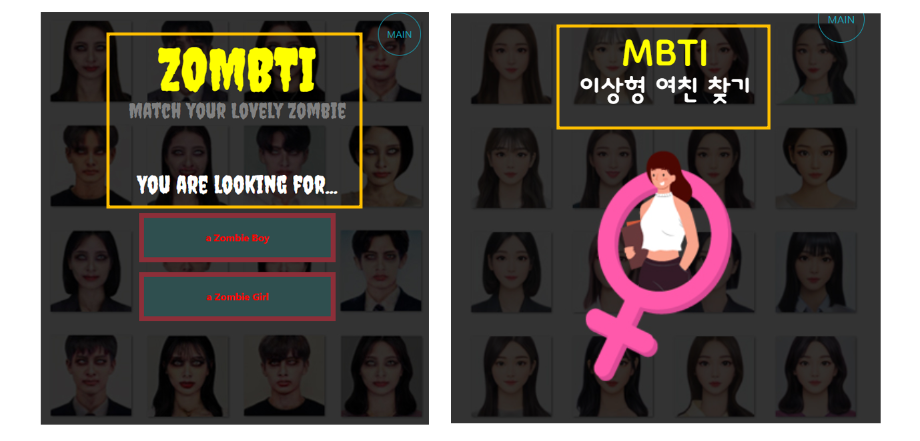
회사를 소개하는 오피셜한 홈페이지에서는 이렇게 독특한 폰트를 사용할 경우가 거의 없겠지만, 게임을 만들거나 독특한 분위기가 필요한 앱을 만들 때에는 폰트 하나만 바꿔줘도 인상이 확~ 달라지는 효과를 쉽게 가질 수 있습니다.
구글 폰트를 사용하면 좋은 점들
Google Fonts를 사용하면 다음과 같은 좋은 잇점들이 있습니다.
Sentence 입력란에 확인하고 싶은 글자를 타이핑해보면, Custom이라고 표시되면서 하단에 다양한 폰트로 적용된 예제들을 확인할 수 있습니다.
한글 폰트를 살펴보기 위해, Language 선택란에서 Korean을 선택했습니다. 그리고 한글로 예시용 문자를 입력했고 폰트 사이즈를 변경하면서 마음에 드는 폰트를 찾으면 됩니다.
약 1500여 개의 구글 폰트 중 한글 폰트는 31개 밖에 없다는 게 무척 아쉽습니다.
좀비티아이(ZOMBTI) 앱에서 타이틀로 사용한 폰트 이름은 Creepster 입니다.
마음에 드는 폰트를 발견했으니, 클릭을 해줍니다.
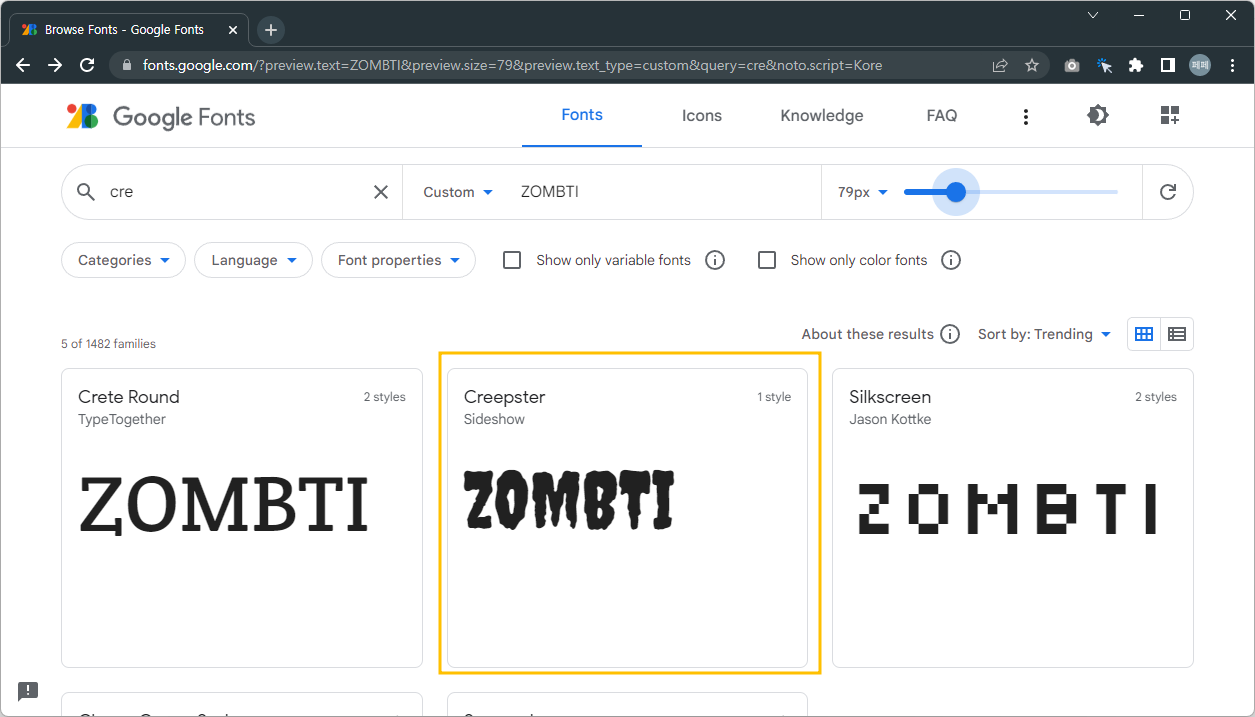
Creepster 폰트에 대한 상세 페이지가 나타납니다.
Creepster 폰트는 Regular 400 폰트 하나만 제공하는 것 같습니다. 보통 글자의 굵기에 대한 정보라고 이해하시면 됩니다.
폰트 사용을 위해 Select Regular 400 버튼을 클릭합니다.
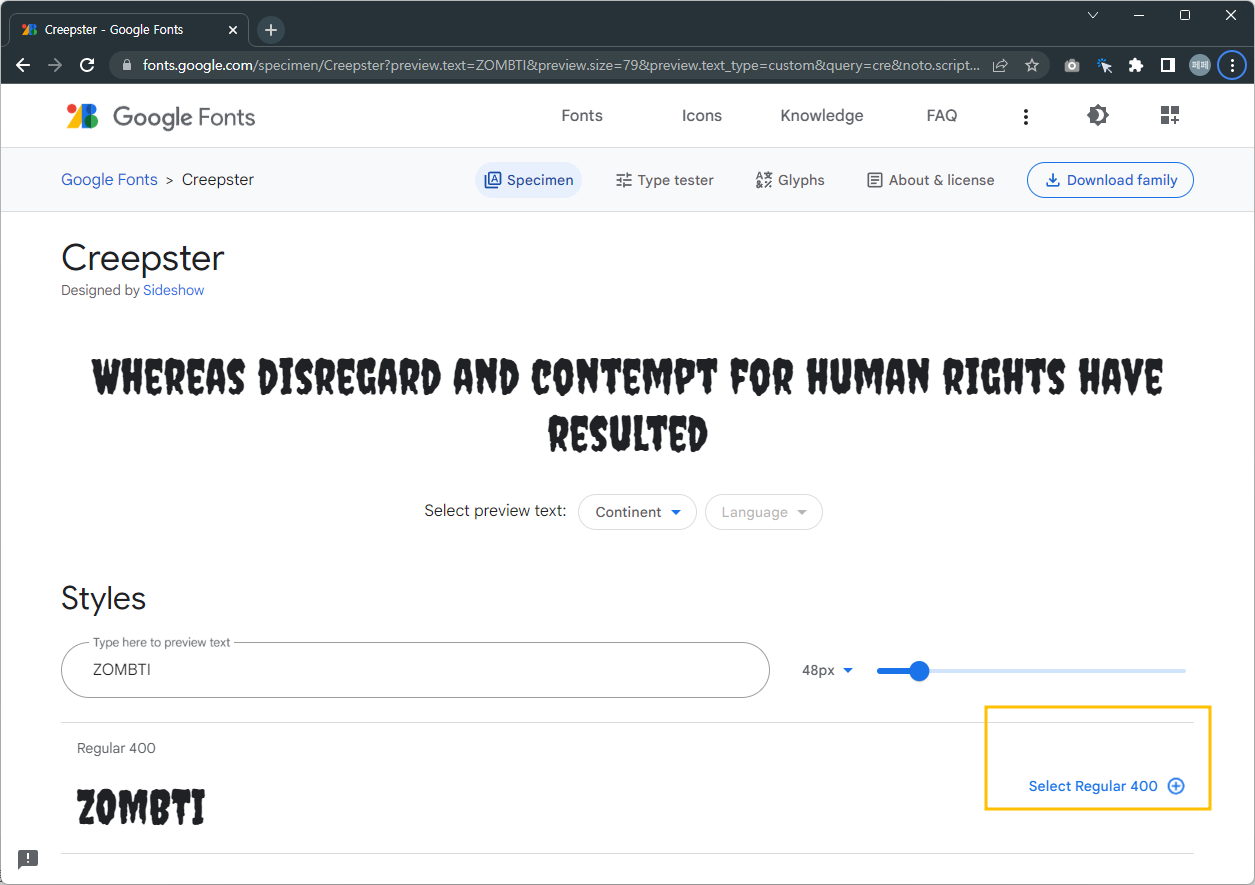
폰트 속성과 숫자의 의미
참고로폰트들은 일반적으로 다양한 굵기를 가지고 있는데요, 대개 다음과 같은 의미를 지닙니다.
- lighter (100-300) : normal 보다 얇은 굵기
- normal (400) : 기본(Regular) 굵기
- bolder (600-900) : normal 보다 굵은 굵기
- bold (700) : bold, 두꺼운 굵기
100 ~ 900까지 숫자 값으로 굵기를 설정하게 되는데, 100이 제일 얇고 900이 제일 굵습니다.
(모든 폰트가 이 값을 가지고 있지는 않고, 폰트 마다 다릅니다.)
Select Regular 400 버튼을 클릭하면, 브라우저 오른 쪽 탭이 열리면서(마치 장바구니 처럼!) Use on the web 섹션이 나타납니다. 구글 폰트를 실제로 웹문서에 적용하는 방법을 친절하게 설명해주고 있습니다.
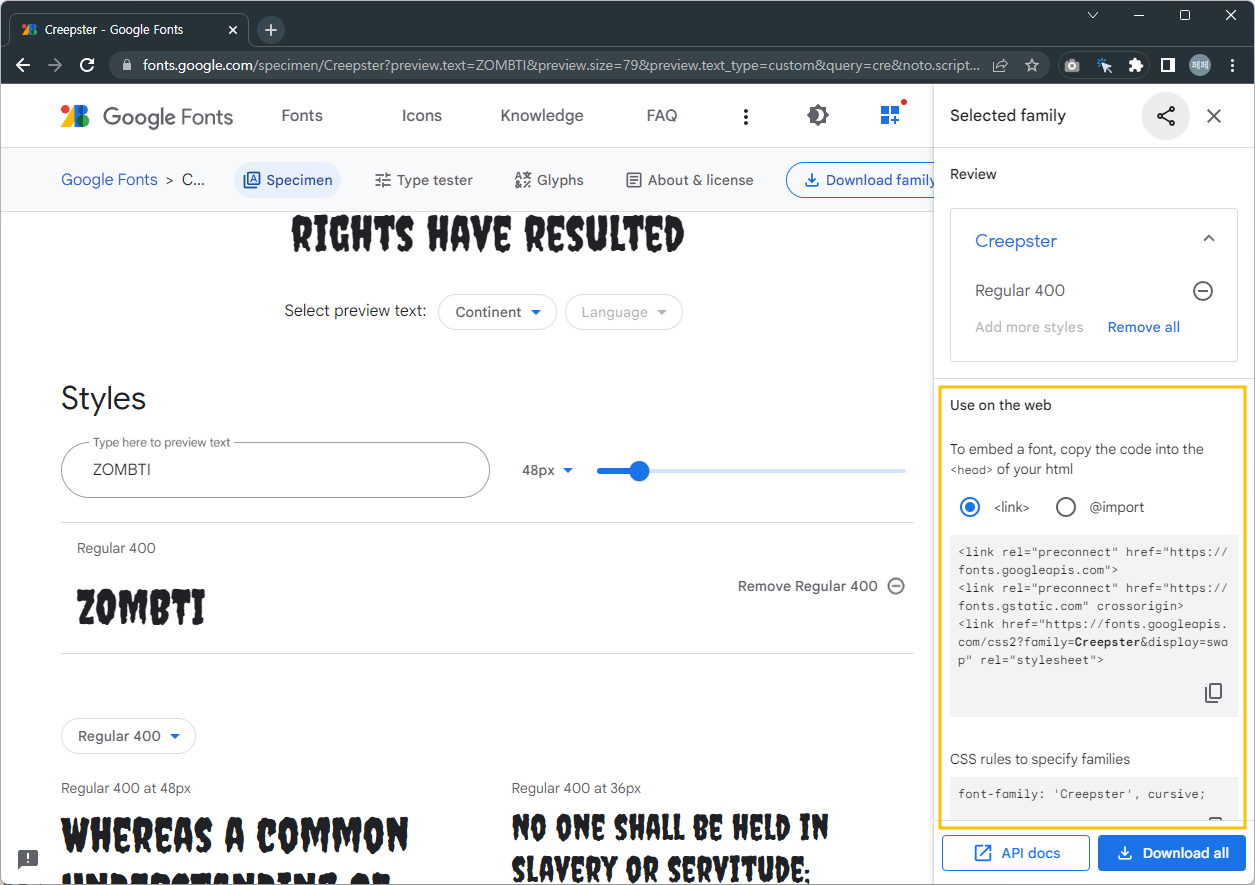
브라우저를 새로고침 해보면, 쨘~ 폰트가 좀비 분위기 물씬하게 변경되었습니다. 쉽죠?^^
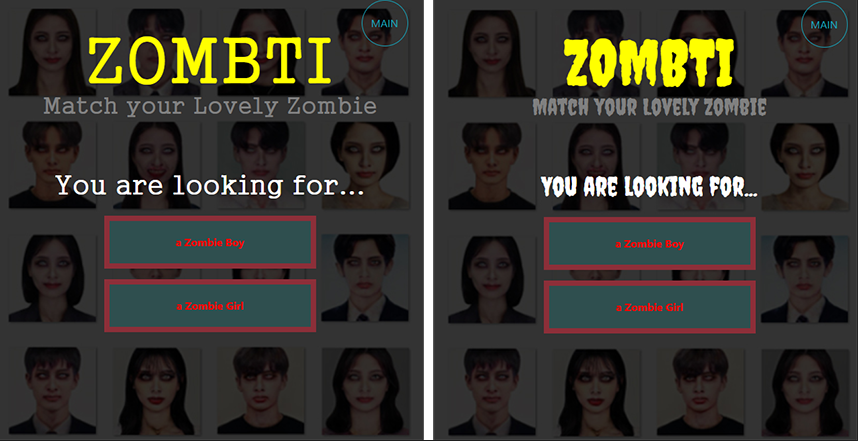
아래는 다른 폰트를 적용해본 예입니다. 동글동글 귀여운 한글 폰트를 찾아서 적용해보았더랬습니다.
마치며